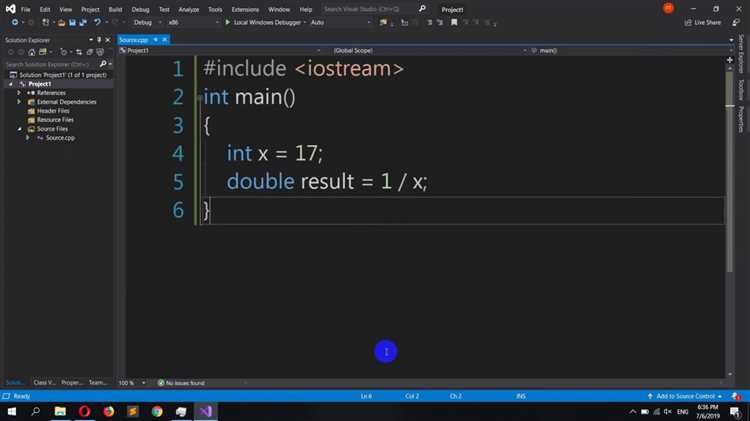
Настройка интерфейса среды разработки влияет на скорость работы и восприятие кода. В Visual Studio можно установить любой совместимый шрифт, чтобы изменить отображение текста редактора. Поддерживаются форматы .ttf и .otf. После установки шрифта в систему его потребуется подключить в настройках редактора.
Далее откройте Visual Studio, перейдите в меню Tools → Options. В разделе Environment → Fonts and Colors выберите пункт Text Editor в выпадающем списке Show settings for. В поле Font появится установленный шрифт. Выберите его и примените изменения. Настройки вступают в силу сразу без перезапуска среды.
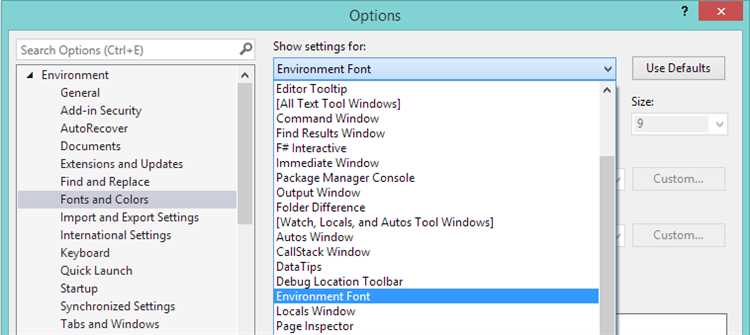
Для настройки комфортной работы с кодом в Visual Studio рекомендуется использовать специализированные моноширинные шрифты, обеспечивающие читаемость и визуальное различие символов. Скачать их можно на проверенных ресурсах без регистрации и рекламы.
Как найти установленный шрифт в настройках Visual Studio
Откройте Visual Studio и перейдите в меню Tools – Options. В появившемся окне раскройте раздел Environment, затем выберите пункт Fonts and Colors.
В правой части окна отыщите выпадающий список Font. Здесь отображаются все установленные в системе шрифты, доступные для использования в редакторе кода и других элементах интерфейса Visual Studio.
Чтобы узнать, какой шрифт используется в данный момент, обратите внимание на значение в списке Font, установленное по умолчанию или ранее выбранное. Ниже, в списке Show settings for, можно выбрать конкретный элемент интерфейса, например Text Editor, чтобы проверить или изменить шрифт именно для него.
Как изменить шрифт редактора кода в Visual Studio
Для настройки шрифта редактора в Visual Studio выполните следующие действия:
- Откройте меню Tools и выберите Options.
- В открывшемся окне перейдите в раздел Environment → Fonts and Colors.
- В выпадающем списке Show settings for выберите пункт Text Editor.
- В списке Font выберите нужный шрифт. Рекомендуется использовать моноширинные варианты: Fira Code, JetBrains Mono, Consolas, так как они обеспечивают равномерное отображение символов.
- Установите подходящий размер в поле Size. Оптимальное значение – от 12 до 14 пунктов для Full HD дисплея. Для экранов с высоким DPI может потребоваться увеличение размера.
- При необходимости настройте цветовую схему в списке Item foreground и Item background, чтобы повысить читаемость.
- Нажмите OK для применения изменений.
Если новый шрифт не отображается в Visual Studio, возможно, причина в том, что приложение не было перезапущено после установки шрифта. Visual Studio загружает список доступных шрифтов при запуске, поэтому после установки нового шрифта нужно закрыть и снова открыть программу. Если это не помогло, стоит проверить, поддерживается ли шрифт для использования в редакторе (некоторые декоративные шрифты могут не поддерживаться). Также проверьте, установлен ли шрифт для всех пользователей или только для текущего — для корректной работы лучше выбирать системную установку для всех пользователей.